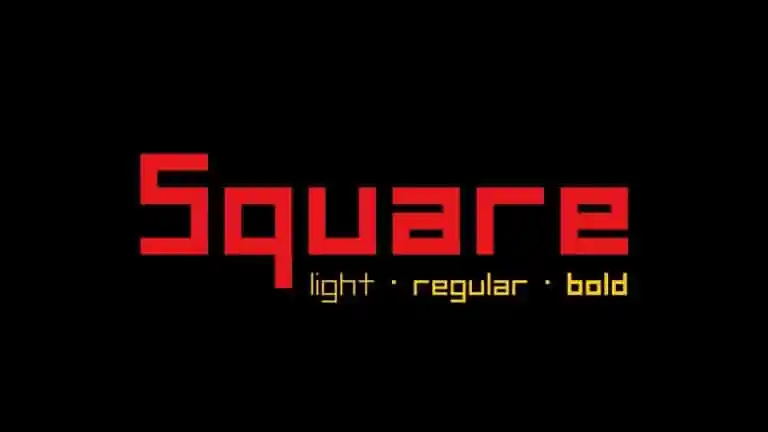
Aqui está uma versão adaptada para a descrição da página de download da font ‘Square Display Font’ que segue as orientações: Square Display Font é uma família tipográfica geométrica com três pesos de corpo, projetada para transmitir um ar forte e futurista. Suas formas têm contornos quadrados, resultando num visual marcante e desafiadormente contemporâneo. Perfeita para aplicações que abordam temáticas inovadoras, tecnologia ou arte, esta fonte é adequada tanto para uso em grande escala quanto para elementos de marca, títulos e textos curtos. Ideal para aplicar em web headlines, gráficos publicitários ou qualquer outro tipo de mídia visual que exija um impacto imediato. Suas linhas retas e formas geométricas também podem complementar perfis, portais ou sites que buscam uma linguagem moderna e futurista. Square Display Font oferece a oportunidade de transformar sua marca em um lembrete marcante do início à frente, seja no ambiente físico ou digital. Esta fonte é perfeita para aqueles buscando uma tipografia única e inovadora que transmita velocidade, determinação e estilo contemporâneo. E com seu peso variado, ela pode ser adaptada de forma a combinar harmoniosamente em múltiplas aplicações sem comprometer sua presença forte na página ou mídia. Seja para o seu próximo projeto editorial, web design ou qualquer aplicação visual que necessite de uma fonte poderosa e moderna, Square Display Font é um excelente recurso gráfico a adquirir.